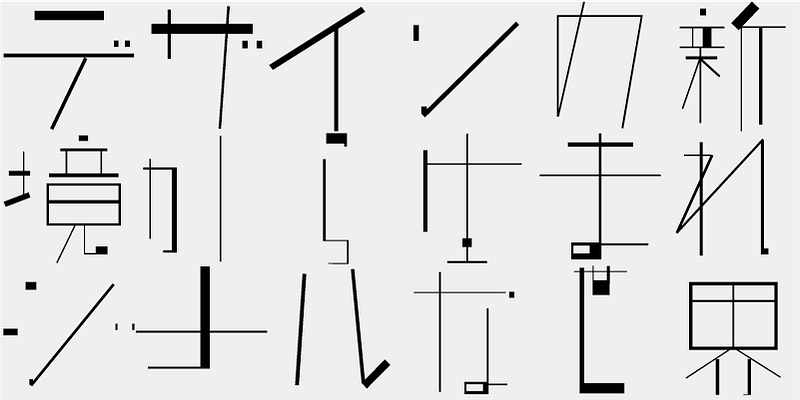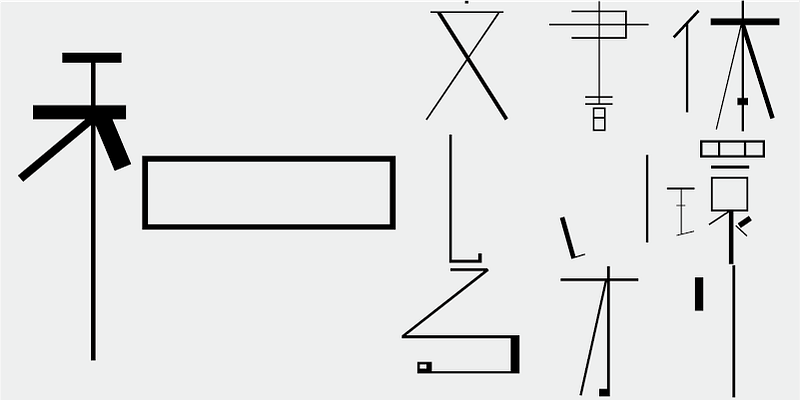
Dies ist meine erste Schrift mit einer freiheitlichen Stimmung. Durch die Entwicklung dieser Schrift ist mein Interesse an der Erstellung von Buchstabenformen, am Schriftsatz und an der Verwendung durch andere gewachsen.
Diese Schrift umfasst 1.000 wichtige Kanji-Zeichen, die aus einer von Zeitungen, Verlagen und Forschungsinstituten für Linguistik erstellten Tabelle der häufigsten Zeichen ausgewählt wurden, plus 206 Kana-Zeichen und Interpunktion.
In der heutigen japanischen Schriftproduktion gelten die 7.000 Zeichen des JIS-Standards als unabdingbar. Aber brauchen alle Schriften wirklich 7.000 Zeichen? Im Zeitalter des Fotosatzes wurden weit weniger Zeichen benötigt. FONT1000, eine Gruppe unabhängiger Schriftdesigner, ging von dieser einfachen Frage aus. Wir haben die mindestens 1.000 (ideografischen) Kanji-Zeichen ausgewählt, die für den Satz in Japanisch erforderlich sind, und aktiv Schriften und Schriftbilder dafür entworfen. Dieser 1000-Kanji-Zeichensatz wurde unter Verwendung von Zeichenhäufigkeitsdaten ausgewählt, die u. a. von Zeitungsunternehmen, Verlagen und Sprachforschungsinstituten zusammengestellt wurden, und enthält auch Kana-Silbenzeichen und Satzzeichen. FONT1000 begann 2001 mit 25 Designern und 25 Schriften. Heute haben wir 130 Schriften und sind auf fast 40 Mitglieder angewachsen, sodass wir an Schriften mit mehr Zeichen arbeiten können.